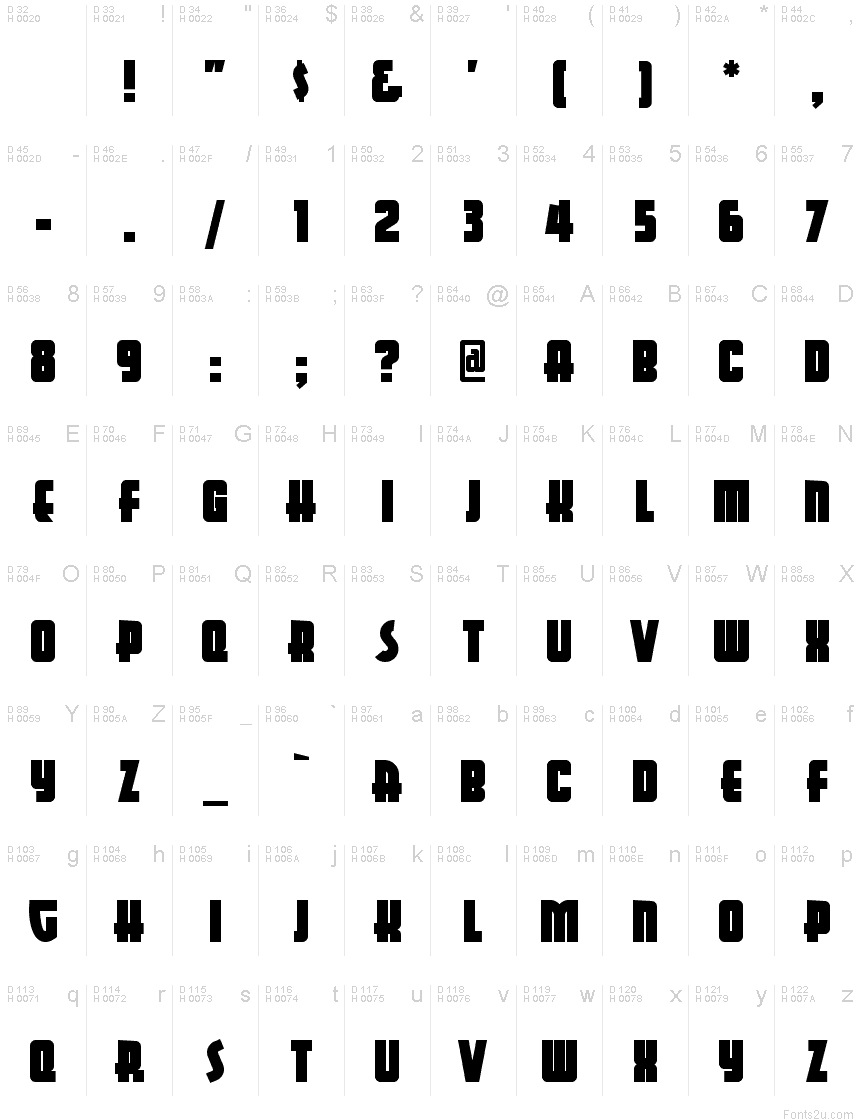
AerojonesNF
Aerojones NF autorstwa Nicka Curtisa to darmowy, utrzymany w stylu retro font typu display, który wygląda, jakby został zespawany z masywnych stalowych płyt. Wysokie, ciasno ustawione litery, kanciaste kształty i gwałtowne krzywizny tworzą odważny, industrialny rytm, przywodzący na myśl zarówno automaty arcade, jak i literaturę sci-fi klasy pulp. Czarne, blokowe formy zazębiają się niczym w siatce, sprawiając, że każde słowo uderza w stronę lub ekran z ciężkim, satysfakcjonującym efektem.
Używając Aerojones NF, zyskujesz wyrazisty, pewny głos, który świetnie sprawdza się na plakatach, logotypach gier i automatów, tytułach science fiction, brandingu sportowym, ulotkach eventowych oraz przy projektach opakowań. Ten darmowy font pokazuje swój potencjał w dużych rozmiarach, gdzie jego gęste kształty i ostre krawędzie robią największe wrażenie. W przypadku tekstów pomocniczych, zestaw go z lekkim, czystym bezszeryfowym krojem geometrycznym, aby zachować czytelność, podczas gdy Aerojones NF przejmuje rolę głównego akcentu.